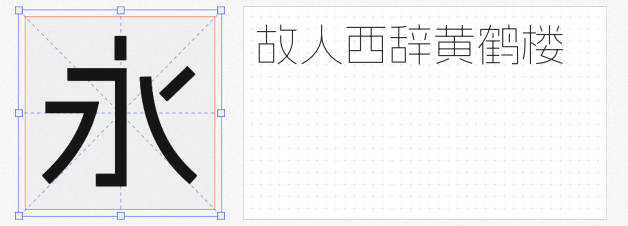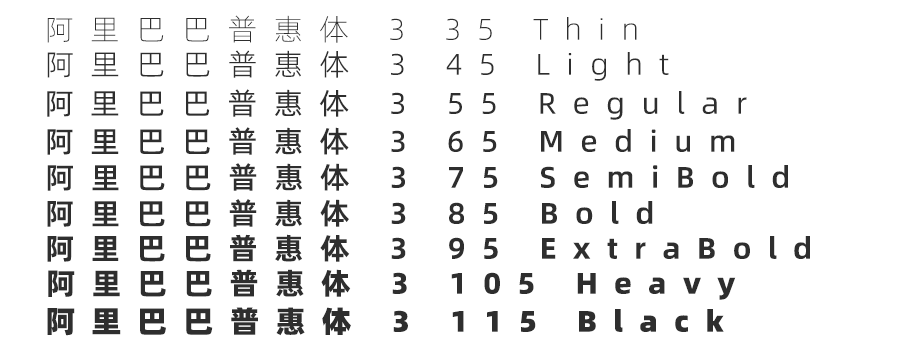
在商业设计中,标题字体是传递品牌调性、吸引用户注意的核心元素。然而,版权问题常让设计师陷入“用字焦虑”。今天推荐四款免费可商用的标题字体,它们风格鲜明、适用场景广泛,助你轻松打造高辨识度设计作品。
阿里妈妈数黑体以“饱满中正”的字体结构奠定视觉基础,笔画厚实简练却不失灵动,布白间暗藏现代韵律。其独特之处在于巧妙融合“图形感”与“书写感”:既保证远距离阅读的清晰度,又通过笔画末端的微妙弧度增添人文温度。无论是科技产品海报的标题,还是时尚杂志的封面字,数黑体都能以先锋气质脱颖而出,尤其适合需要强调“未来感”与“专业度”的场景。
阿里妈妈方圆体VF创新性地将黑体与圆体整合为可变字体,黑体延续数黑体的现代骨架,圆体则以圆润弧线传递亲和力。设计师可通过调整字重与圆角参数,一键切换“硬核科技”与“萌系潮流”风格。这种灵活性使其成为电商大促主视觉、社交媒体创意海报的“万能钥匙”,尤其适合需要快速适配多平台、多主题的商业项目。
阿里巴巴普惠体3.0 以“瘦高重心”的字体造型,精准捕捉Z世代审美偏好。标题字通过省略笔画出脚、简化装饰性细节,实现“极简而不单调”的视觉效果。这款字体自带“青春活力”滤镜,无论是新消费品牌的包装标题,还是互联网产品的slogan呈现,都能以轻盈姿态传递品牌年轻化态度。
从传统刷墙字体中提取灵感,乡立方黑体以粗犷有力的笔触重构乡村视觉语言。笔画转折处保留手工书写痕迹,字面空间疏密有致,既保留乡土文化的质朴感,又通过现代化设计手法提升传播效率。这款字体是乡村振兴项目、地方文旅宣传的绝佳选择,用设计语言讲述“新乡村故事”。